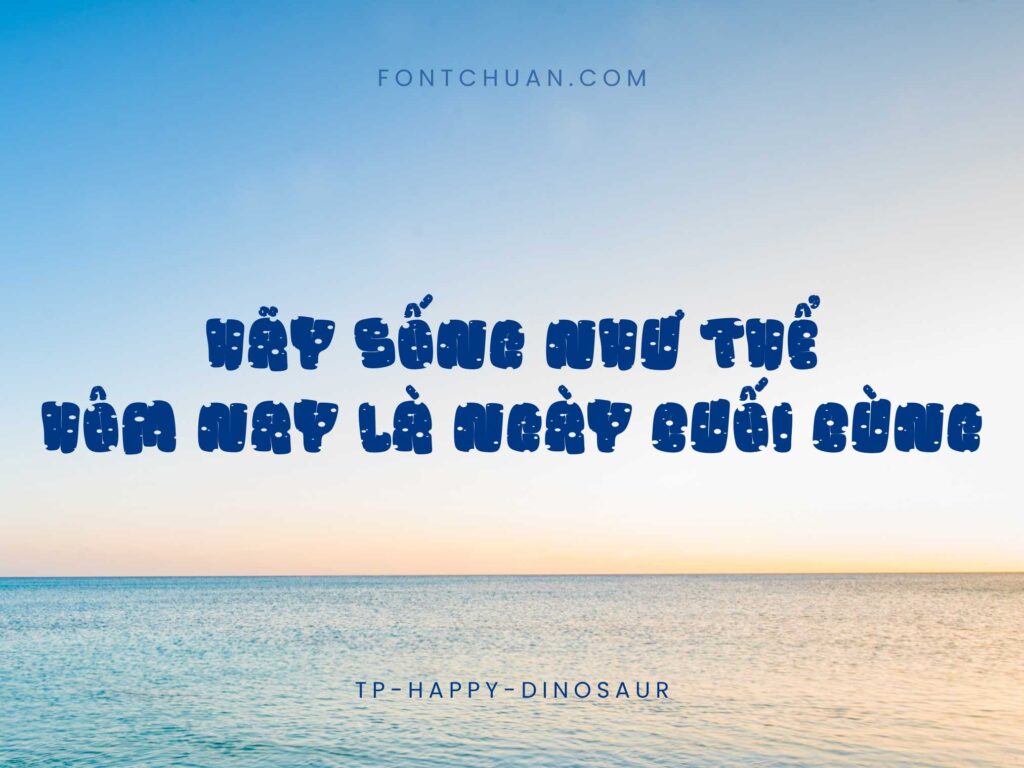
Font TP Happy Dinosaur Việt Hóa
Happy Dinosaur là một font chữ trưng bày với các ký tự đậm và tròn trịa, tạo cảm giác vui tươi và thân thiện. Thiết kế của font này phù hợp cho các dự án liên quan đến trẻ em, thương hiệu vui nhộn hoặc các ấn phẩm giáo dục. Font đã được Việt hóa để hỗ trợ tiếng Việt bởi Tuỳn Pucca, giúp mở rộng phạm vi sử dụng cho người dùng Việt Nam. Font này được sưu tầm và chia sẻ bởi thành viên của Font Chuẩn, đáp ứng nhu cầu sử dụng trong các dự án thiết kế đa dạng.
Đặc điểm thiết kế của Happy Dinosaur bao gồm các chữ cái tròn trịa và ngộ nghĩnh, tạo nên sự thân thiện và hấp dẫn cho các dự án thiết kế. Font này phù hợp cho các ứng dụng như sách thiếu nhi, thương hiệu vui tươi, thiệp mời dự tiệc và poster không chính thức. Các ngành nghề phù hợp bao gồm giáo dục, quảng cáo và thiết kế đồ họa.